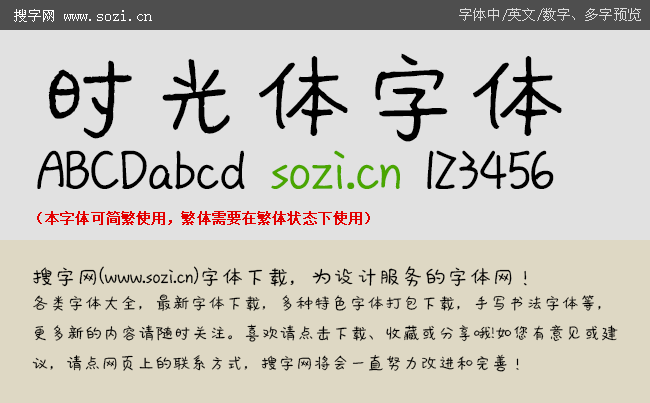
時(shí)光體字體
搜字網(wǎng)給大家提供一款很卡通的手寫風(fēng)格手機(jī)中文字體下載。修改者將它命名為時(shí)光體字體,這款手機(jī)字體是是仿照兒童手寫風(fēng)格的卡通手寫字體。即有卡通字體的趣味性,又有手寫字體的藝術(shù)性,特別適合喜歡手機(jī)字體個(gè)性一些的朋友在手機(jī)上安裝使用。